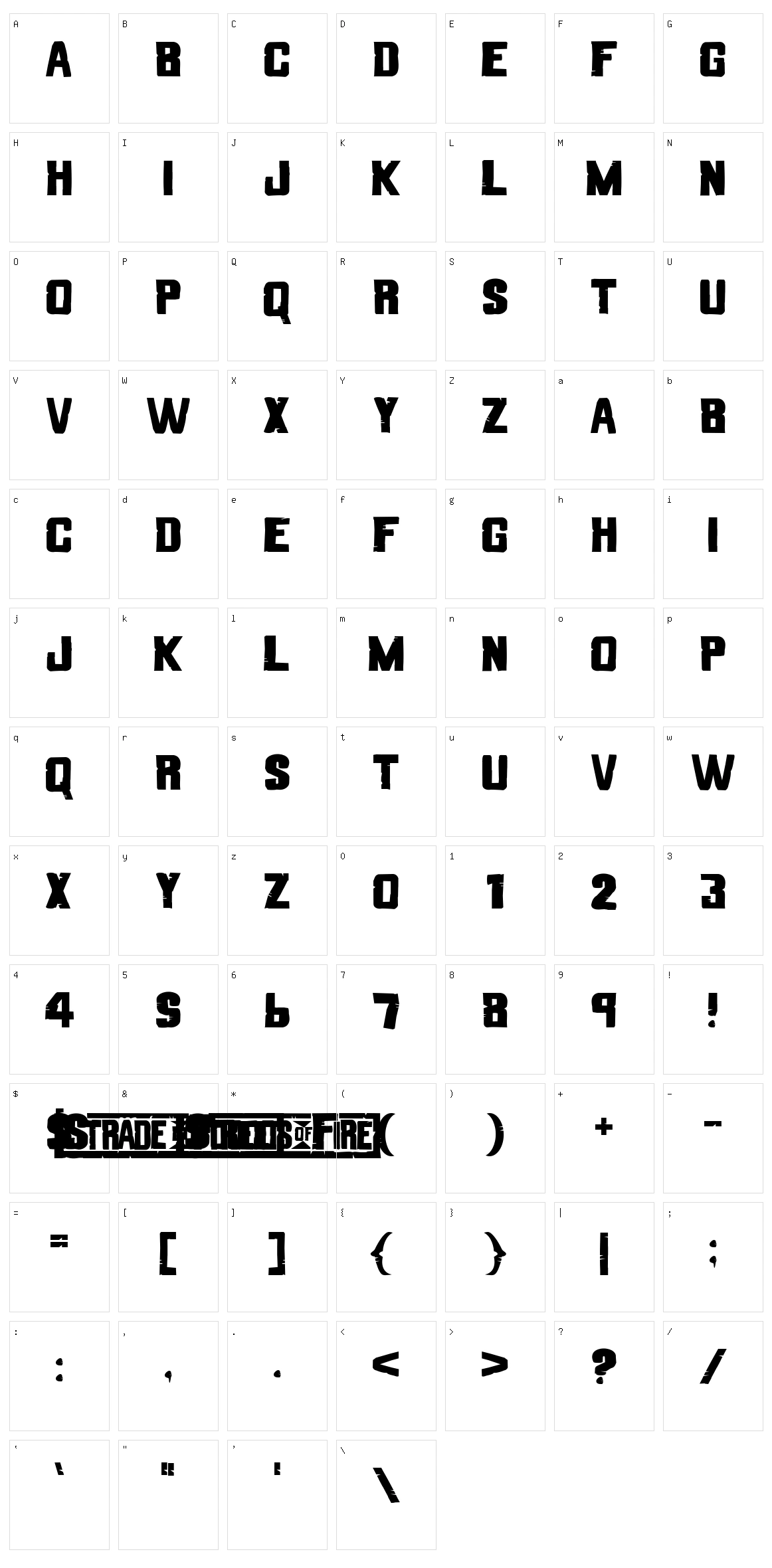
x STRADE DI FUOCO FONT x
Font name: STRADE DI FUOCO (Diane Lane Collection) - Latin Decorative font (versione 1.0)
Type designer: P. A. Vannucci
STRADE DI FUOCO font: direttamente dal film diretto da Walter Hill e interpretato da Diane Lane, il font inedito per tutti
gli estimatori del film. Da notare il ritocco necessario in Photoshop per conferire, alla titolazione, l'originale bordatura.
STREETS OF FIRE font: directly from the Best movie by Walter Hill, with Diane Lane,
the original font for all lovers. Use ADOBE Photoshop for the original border from title.